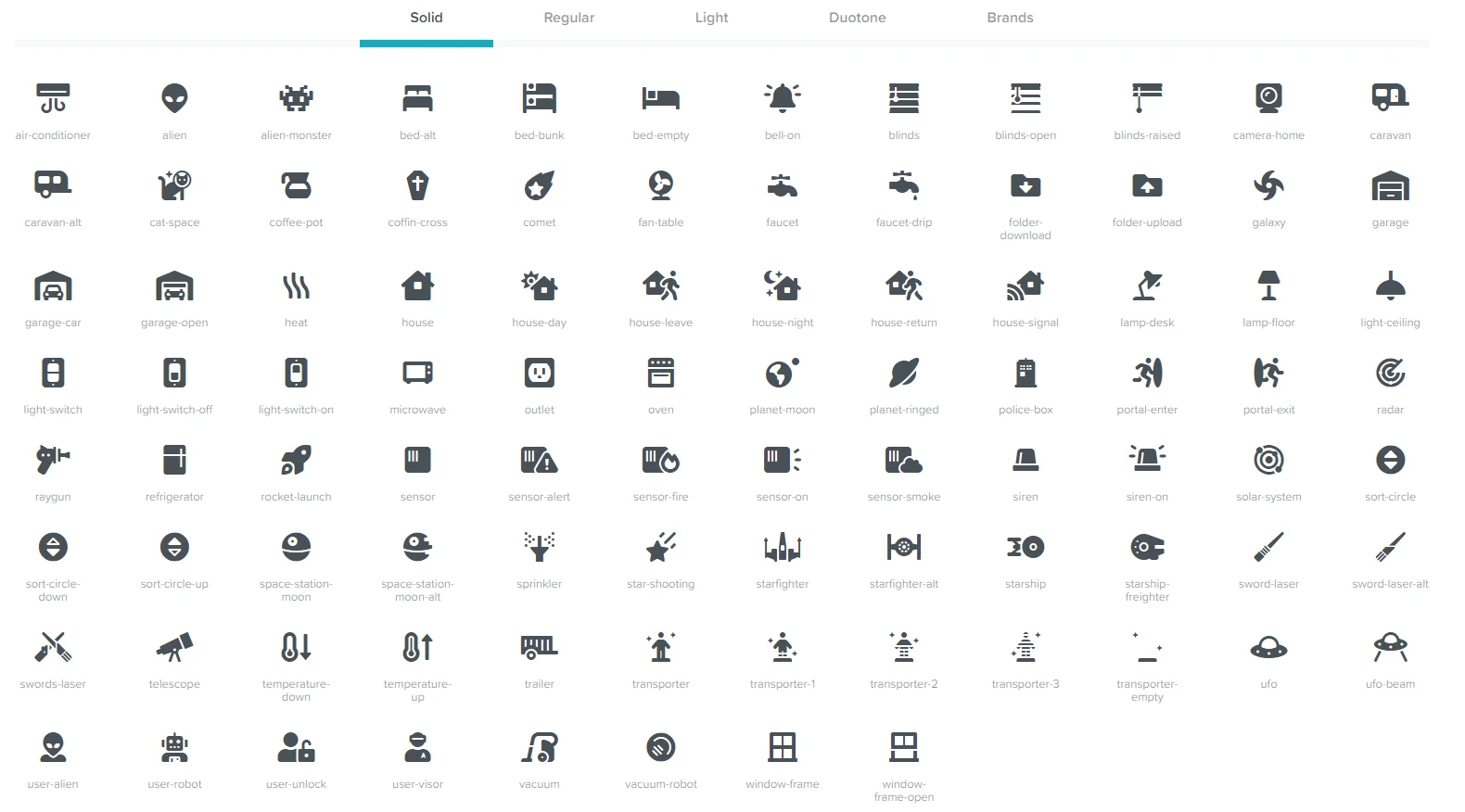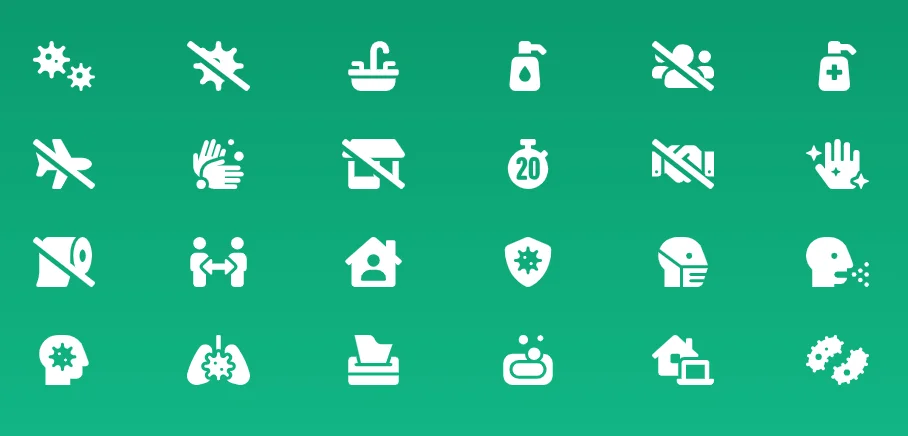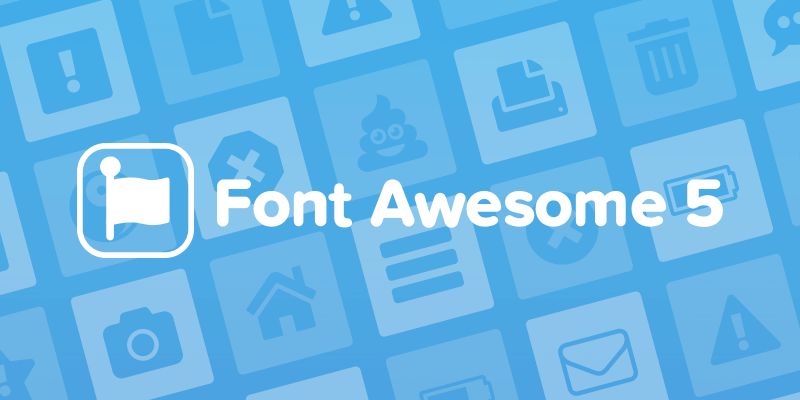
Font Awesome Pro là phiên bản mới của biểu tượng phông chữ và công cụ CSS.
Font Awesome PRO cung cấp cho bạn các biểu tượng vector có thể mở rộng mà bạn có thể dễ dàng cá nhân hóa – kích thước, màu sắc, bóng và mọi thứ bạn có thể làm với CSS. Trong phiên bản 5.13.0 mới, 120 biểu tượng đã được thêm vào.
Đặc biệt: COVID-19: Free Awareness Icons giúp thông báo về các khuyến nghị vệ sinh và các sáng kiến ​​khác để chống lại COVID-19! Sử dụng các biểu tượng này trong các dấu hiệu, lời nhắc, ứng dụng theo dõi…
• Những cải tiến nổi bật Font Awesome Pro Version 5.13 (Web/Desktop)
• COVID-19: Free Awareness Icons
COVID-19 Free Awareness Icons
• Đối tượng phông chữ không xác định
Đã đến lúc đột kích Khu vực 51? Nhà phát triển đã thêm rất nhiều biểu tượng ngoài hành tinh.
Font người ngoài hành tinh - Font Awesome Pro
• Các biểu tượng thiên hà, ngân hà
Chúng ta đã sẵn sàng cho giới hạn cuối cùng trong một thiên hà xa, rất xa.
Font thiên hà - Font Awesome Pro
• Biểu tượng hộ gia đình mới
Làm mới ngôi nhà của bạn với bộ sưu tập các biểu tượng gia đình mới.
Font hộ gia đình - Font Awesome Pro
• Phiên bản Font Awesome Pro v5.13 bao gồm 7842 biểu tượng icons cao cấp và 4 Styles — SolidRegularLight, & Duotone!
Bộ công cụ biểu tượng phổ biến nhất của Internet đã được thiết kế lại và xây dựng từ đầu. Trên hết, các tính năng như chữ ghép biểu tượng, khung SVG, gói NPM chính thức cho các thư viện phổ biến như React và truy cập vào CDN mới.
377 biểu tượng icons Font Awesome Pro